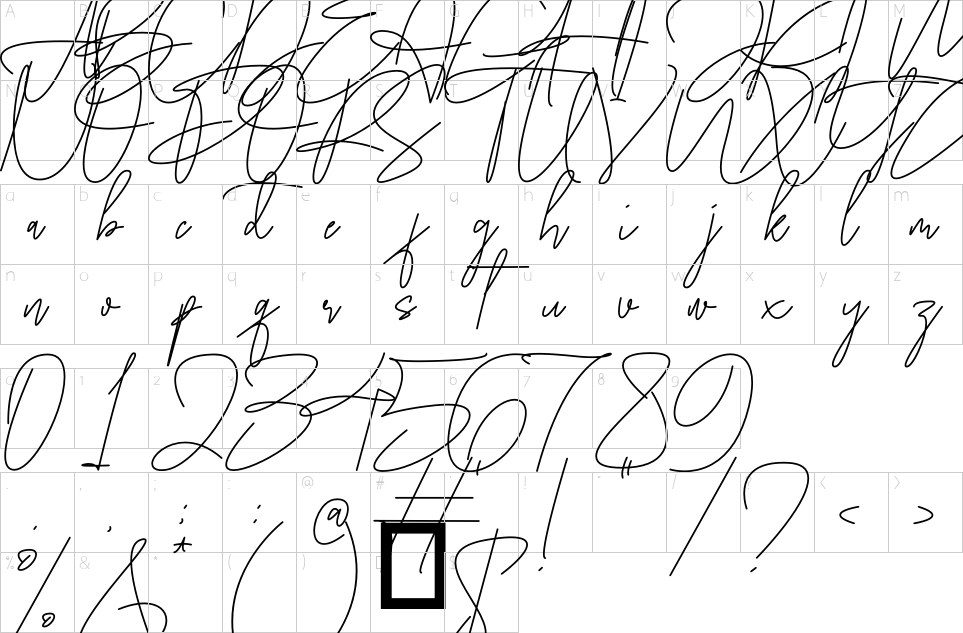
Antasarya Font – Download Grátis
A fonte Antasarya é um recurso grátis para designers de nível intermediário, projetada por Jada Akbal. Suavemente elegante e sofisticada, Antasarya é perfeita para quem busca uma fonte com um charme único e versátil. Composta de linhas elegantes e um design minimalista, a Antasarya oferece uma excelente legibilidade e uma variedade de usos, seja para rótulos de produtos, design editorial, ou até mesmo para criar logotipos. Com o download de apenas 912 vezes, é evidente que muitos designers encontraram o mesmo encanto que você provavelmente irá apreciar ao usar a Antasarya. Se você está buscando uma fonte gratuita que seja versátil e de alta qualidade, Antasarya é uma ótima opção para tornar seus projetos ainda mais distintos.